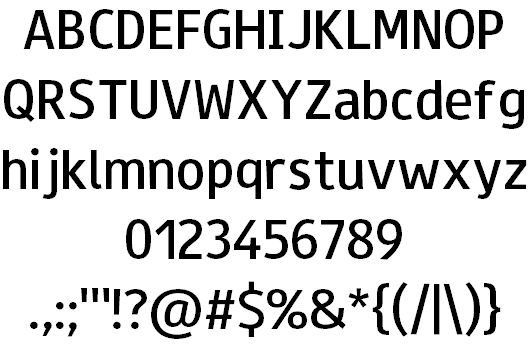
Kostenlose Alternative zur FF Unit
für ein FH-Projekt müsste ich mit der FF Unit arbeiten, die ist aber nicht in meinem Besitz und ich kaufe nicht für eine Wochenaufgabe eine Schrift für huderte Euro ;-):hammer: deswegen wollte ich mal fragen, ob jemand von euch ne freie Alternative wüsste?
Hier das Original:
Ich habe die PleaseOptimize gefunden, aber da passt so einiges nicht … zum Beispiel Q, i und j
Danke :-) die Fira hab ich grad neulich in nem anderen Zusammenhang sogar erst benutzt, ist allerdings schon anders als die Unit und die Rambla ist auch nicht so dicht dran, außerdem brühte ich schon ein paar mehr Schnitte … vielleicht hat ja noch jemand noch eine schlaue Idee, sonst nehme ich einfach Arial oder Comic Sans, wenn schon falsch, dann richtig :hammer::party:
Hier nochmal mein Endergebnis: Es hat sich rausgestellt, dass die Anzeige, die ich nachbauen sollte in der Originalfassung mit der Myriad, die ich hab, gemacht wurde und die Unit-Version aus einer späteren Zeit stammt. Ich konnte das Problem also gut umgehen :-)